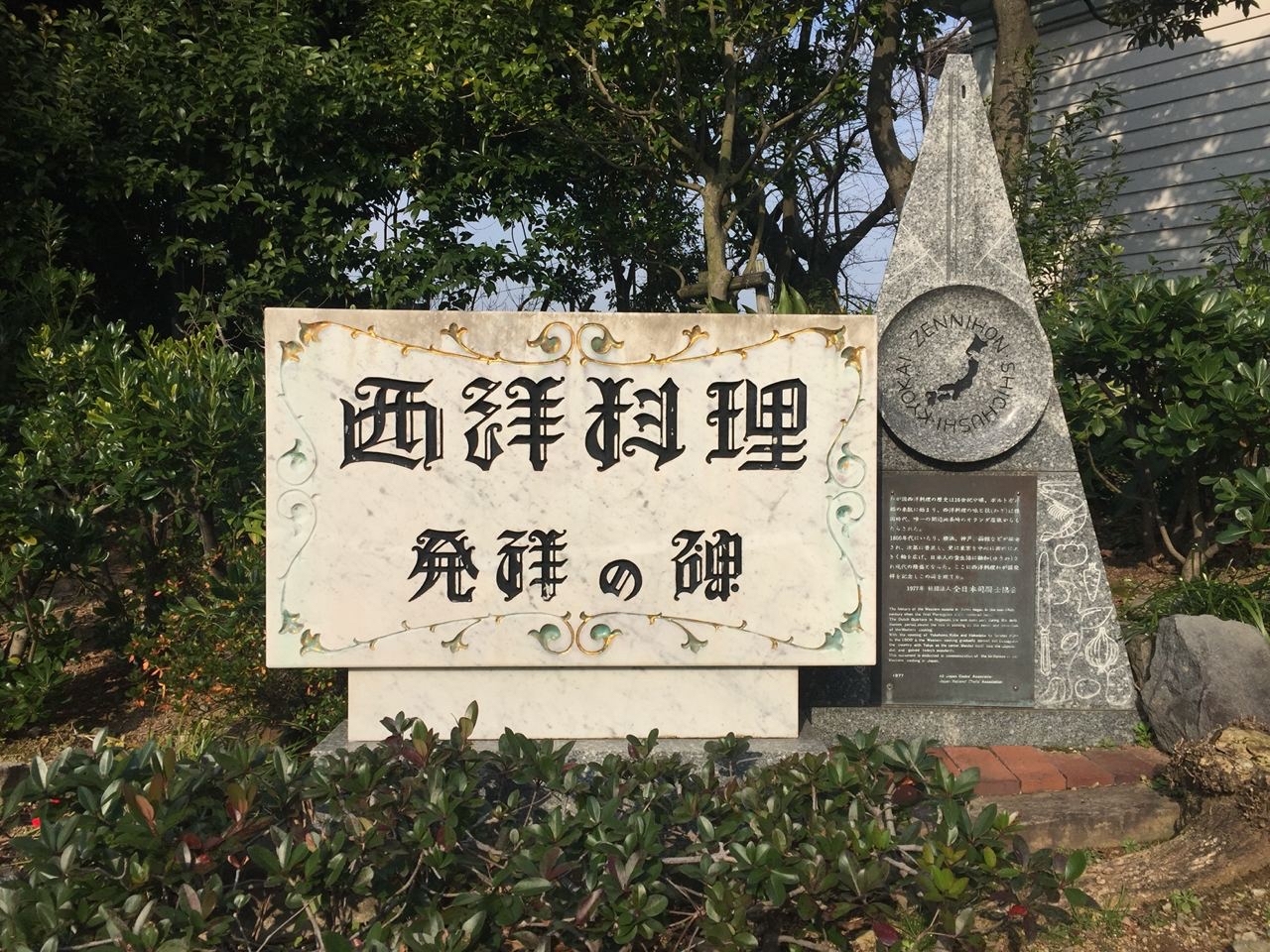
Готический шрифт для японского языка
Если вам интересно, существует ли японский готический шрифт, то вот ответ.
Готический шрифт для японского языка
Это надпись рядом с памятником рождению западной кухни в Японии, который в 1977 году установила в Нагасаки Японская ассоциация шеф-поваров. Памятник стоит рядом с чайной в саду Гловера, на месте которой был самый первый в Японии ресторан западной кухни «Дзиютэй» (自由亭). С тех пор японские шефы достигли в западной кухне выдающихся высот - например, в Токио сейчас 85 ресторанов одной только французской кухни отмечены звездой «Мишлен».